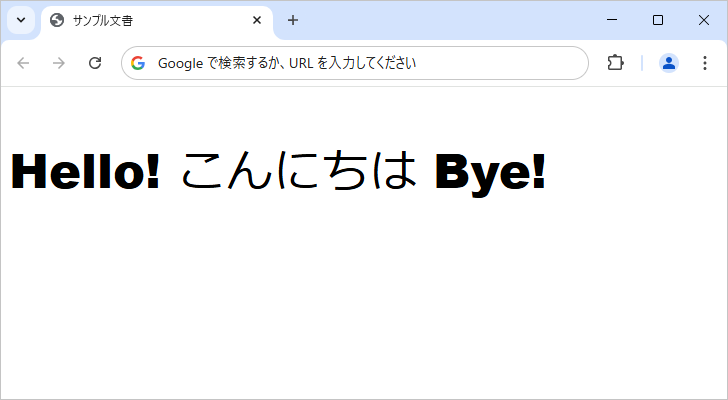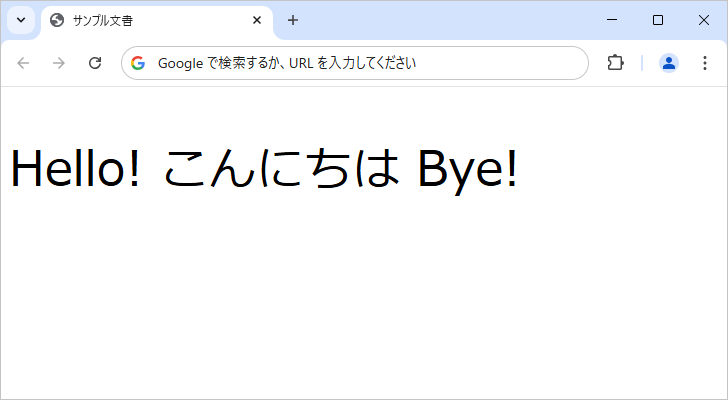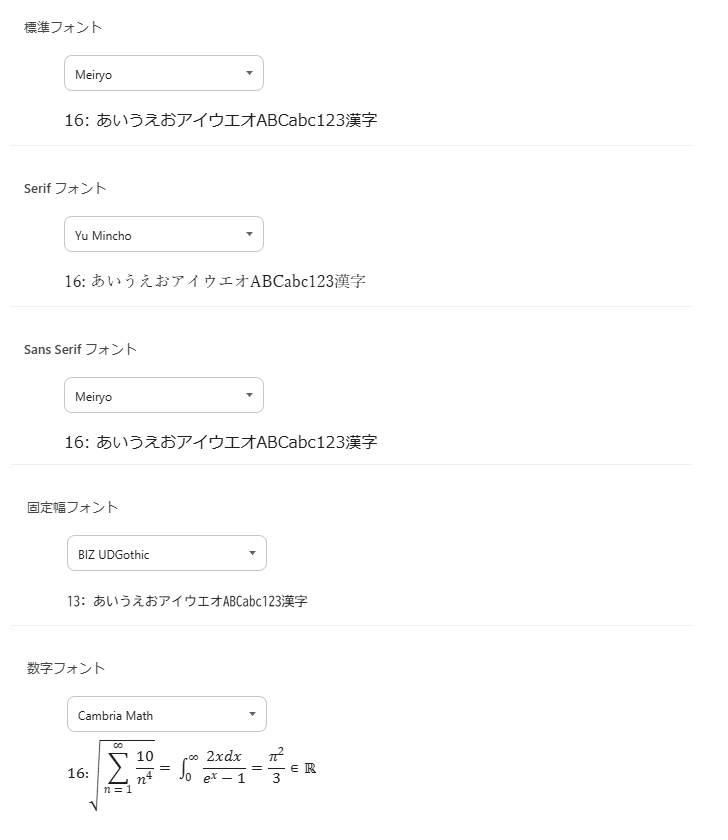
フォントの種類を設定する
Web ページで表示されるテキストのフォントを設定するには、CSS の font-family プロパティを使用します。ホームページを閲覧するユーザーはさまざまな環境からブラウザを使ってアクセスするため、使用できるフォントの種類が異なります。そのため、複数のフォントを設定しておくのが一般的です。ブラウザは、設定されたフォントのリストを順番に確認し、ユーザーの環境で利用できるフォントが見つかった場合に、それを使用します。この記事では、Web ページのテキストに適用するフォントを設定する方法について解説します。
font-familyを使ってフォントの種類を設定する
使用するフォントの種類を設定するには CSS の font-family プロパティを使用します。書式は次の通りです。
セレクタ {
font-family: フォント名1, フォント名2, ..., 総称フォント名;
}
フォント名には具体的なフォント名を設定します。例えば Meiryo や Hiragino Kaku Gothic ProN などです。フォント名を設定する場合、フォント名に空白文字が含まれる場合はシングルクォーテーションまたはダブルクォーテーションで囲って設定してください(今は記述する必要がありませんが、日本語を含むフォント名の場合もクォーテーションで囲みます)。空白を含まないフォント名(例: Meiryo や Arial)は、クォーテーションなしで設定するのが一般的です。
なお font-family プロパティの初期値はブラウザに依存します。
例えば p 要素に対してフォントの種類として Hiragino Kaku Gothic ProN を設定する場合は次のように記述します。
p{
font-family: "Hiragino Kaku Gothic ProN";
}
フォントの種類として Meiryo を設定する場合は次のように記述します。
p{
font-family: Meiryo;
}
注意点として、設定したフォントはユーザーの環境にそのフォントがインストールされていれば使用される仕組みになっています。例えば macOS や iPhone の環境で比較的利用可能なフォントを設定した場合、ユーザーが macOS の環境からブラウザで Web ページを表示すると設定したフォントの種類が使用されますが、 Windows 環境から Web ページを表示すると、設定したフォントが見つからない場合はそのフォントは使用されません。
その為、font-family プロパティでは代替フォントとして複数のフォント名を設定することができます。複数のフォント名を設定する場合はカンマ(,)で区切って続けて記述します。例えば p 要素に対してフォントの種類として "Hiragino Kaku Gothic ProN" と Meiryo を設定する場合は次のように記述します。
p {
font-family: "Hiragino Kaku Gothic ProN", Meiryo;
}
複数のフォント名が設定されている場合、ブラウザは左から順番にフォントが利用できるか確認し、最初に利用可能なフォントを適用します。上記の例ではまず "Hiragino Kaku Gothic ProN" が使用可能か確認し、利用できない場合は Meiryo が適用されます。
また macOS か Windows かだけではなく、iPhone や Android など対象の Web サイトにアクセスする色々な環境を考慮する必要があります。
日本語フォント名と英語フォント名
以前は環境や使用するブラウザによって、日本語フォントの識別名(例: Meiryo)と日本語のフォント名(例: メイリオ)が異なり、正しく適用されないケースがありました。そのため、CSS の font-family プロパティでは、フォント名を設定するときに日本語名と英語フォント名を両方記述するのが一般的でした。
p {
font-family: Meiryo, "メイリオ";
}
しかし、現在の Windows 10 / 11 では、英語フォント名のみ記述すれば問題ありません。例えばメイリオを使用したい場合は、 Meiryo のみを記述すれば十分です。
p {
font-family: Meiryo;
}
総称フォント名
フォントを設定する場合、具体的なフォント名だけでなく、最後に総称フォント名(総称ファミリー名)を設定するのが一般的です。 総称フォント名とは、特定のフォントが利用できない場合に、ブラウザが代わりに選択するフォントのカテゴリを示すものです。 例えば「serif」なら明朝体、「sans-serif」ならゴシック体のフォントが選ばれます(具体的にどのフォントが使用されるかは、ブラウザやOSの設定に依存します)。
総称フォント名には次のようなものがあります。
総称フォント名字体
serif明朝体フォント
sans-serifゴシック体フォント
system-uiOSのUIと同じフォント
monospace等幅のフォント
cursive手書き風の筆記体フォント
fantasy装飾的なデザインフォント
math数式の表示用フォント
総称フォント名として sans-serif を設定した場合、ブラウザに設定されている「ゴシック体」(英語環境では Arial など)が使用されます。どのフォントが適用されるかは、 OS やブラウザのデフォルト設定によります。
例えば次のように記述します。(長いので改行していますが、実際は一行で記述して構いません)。
p {
font-family:
"Hiragino Kaku Gothic ProN",
Meiryo,
sans-serif;
}
総称フォント名は font-family プロパティの最後に記述してください。また、総称フォント名はクォーテーションで囲まずに記述します。クォーテーションで囲んでしまうと、ブラウザが総称フォント名を特定のフォント名として認識しようとするため、正しく適用されない可能性があります。
なお Windows 環境で Chrome のデフォルトのフォントの設定を確認してみると次のようになっています。
総称フォント名(1)
標準フォントと Sans Serif フォントは Meiryo 、 Serif フォントは Yu Mincho 、固定幅フォントは BIZ UDGothic 数字フォントは Cambria Math です。
欧文フォントと和文フォントについて
日本語などを対象とした「和文フォント」は、漢字やひらがなだけでなく、アルファベットや数字、記号も対象となっていることが多いため、基本的にはすべての文字に適用することができます。それに対して、欧米で使用される「欧文フォント」は、英字や数字、記号を対象としたフォントであり、日本語の文字(漢字・ひらがな・カタカナ)には通常適用されません。
数値やアルファベットと、漢字やひらがななどで異なるフォントを設定したい場合は、 font-family プロパティで先に欧文フォントを設定し、その後に和文フォントを設定します。こうすることで、英数字や記号には欧文フォントが適用され、日本語の文字には和文フォントが適用されます。
p {
font-family: 欧文フォント名, 和文フォント名, sans-serif;
}
例えば、次のように記述します。
p {
font-family: Arial, "Hiragino Kaku Gothic ProN", sans-serif;
}
この場合、英字や数字には Arial が適用され、日本語の文字(漢字・ひらがな・カタカナ)には Hiragino Kaku Gothic ProN が適用されます。
反対に、和文フォントを先に記述してしまうと、和文フォントには英数字も含まれているため、すべての文字に和文フォントが適用されてしまいます。例えば、次のように設定すると、英数字も和文フォントで表示されてしまいます。
p {
font-family: "Hiragino Kaku Gothic ProN", Arial, sans-serif;
}
この場合、英数字も日本語も Hiragino Kaku Gothic ProN で表示されるため、意図したデザインと異なる場合があります。 そのため、欧文フォントを先に設定し、その後に和文フォントを設定するのが一般的です。
簡単なテストとして次のような HTML 文書を作成しました。 p 要素に対してフォントを設定しています。(分かりやすいように欧文フォントに Arial Black を設定しています)。
font-family プロパティに対して、最初に Arial Black 、次に Meiryo が設定されているので、アルファベットに対しては Arial Black が使用され、日本語には Meiryo が使用されます。
欧文フォントと和文フォントについて(1)
次に font-family プロパティに対してフォントの設定の順番を変更してみます。
font-family プロパティに対して、最初に Meiryo が設定されているので、日本語だけでなくアルファベットに対しても Meiryo が使用されます。
欧文フォントと和文フォントについて(2)
このようにアルファベットと日本語で異なるフォントを適用したい場合には、 font-family プロパティへフォント名を設定する場合に、先に欧文フォントを設定してから和文フォントを設定する点に注意してください。
p {
font-family: "Helvetica Neue",
Arial,
"Hiragino Kaku Gothic ProN",
Meiryo,
sans-serif;
}
これで font-family プロパティの設定は完了です。
Web ページのテキストに適用するフォントを設定する方法について解説しました。